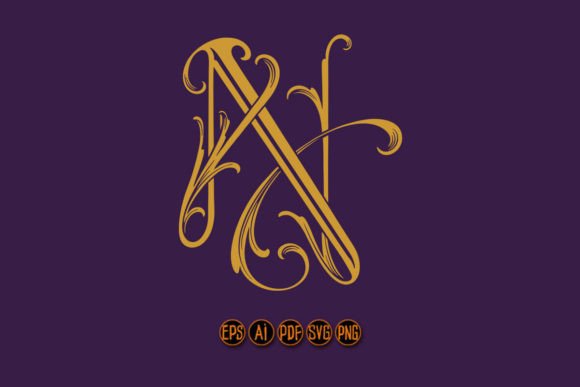
Stately Classic Lettering N Monogram
หากคุณกำลังมองหาเนื้อหาคุณภาพสูงเช่น Stately Classic Lettering N Monogram แพ็คเกจพรีเมียมนี้เป็นตัวเลือกที่ยอดเยี่ยมสำหรับโปรเจ็กต์สร้างสรรค์ของคุณ